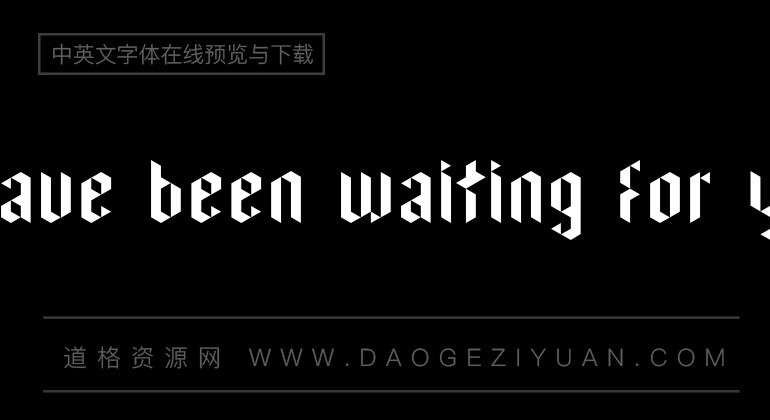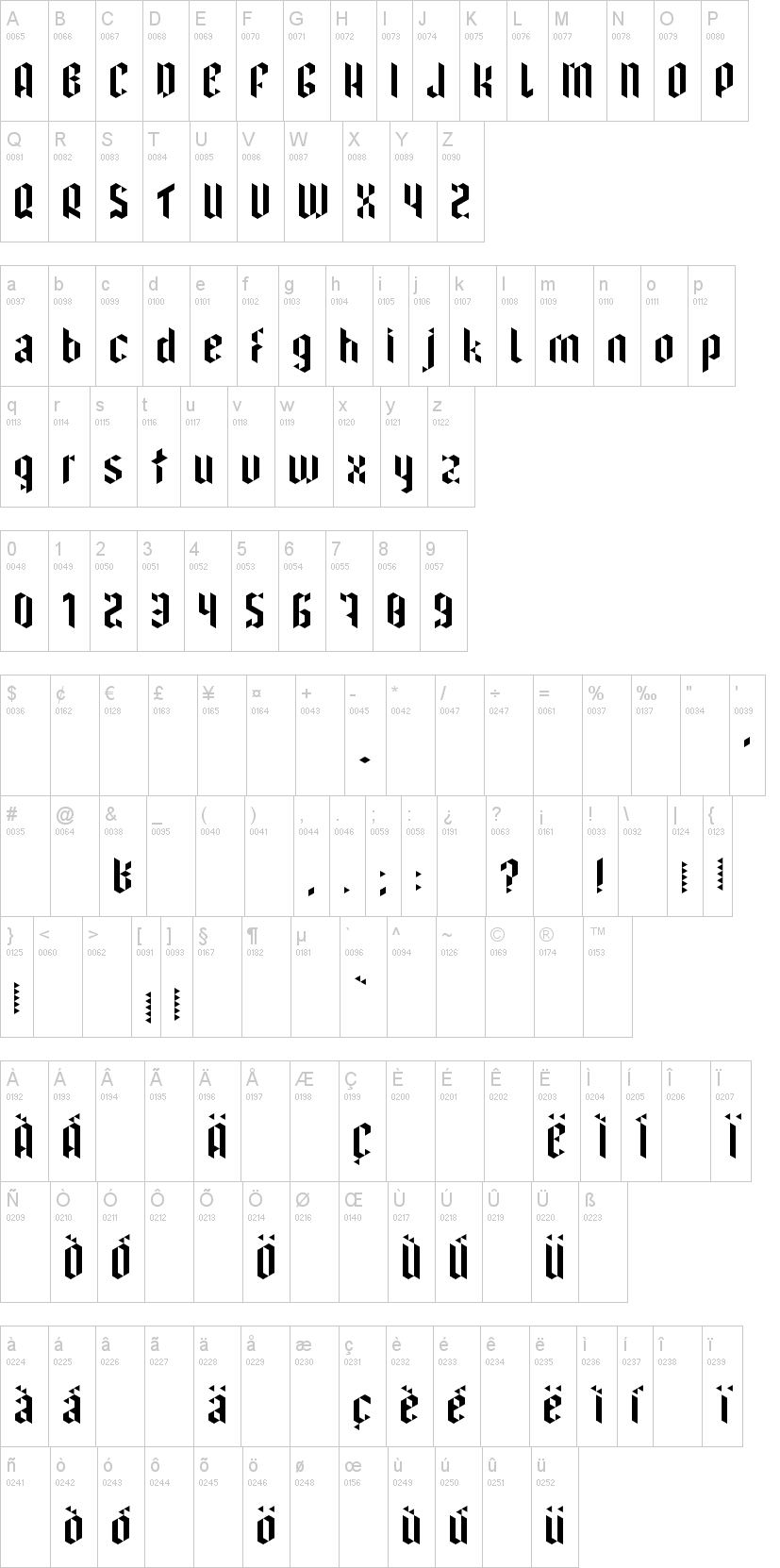
I have been waiting for you
I have been waiting for you是一款非常不错的手写艺术字体,具有很好的视觉感,适合于文化类的宣传设计、商业类品牌的广告和产品包装设计以及个性化文字排版等较多场景。
I have been waiting for you字符映射图